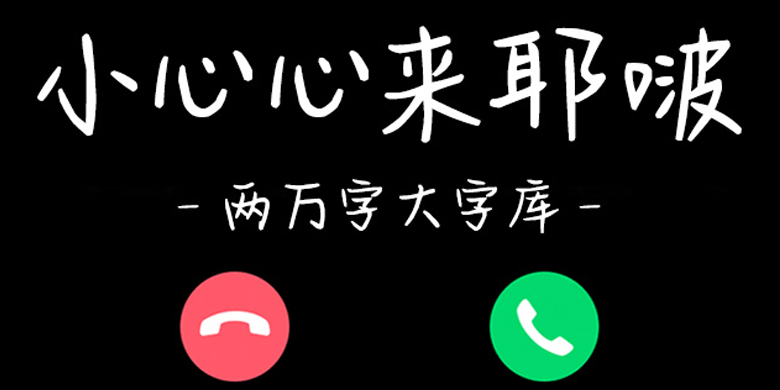
方正手迹-小心心来耶啵
字体品牌: 方正手迹 设计师:余丹 字体分类:常规书写·硬笔 字体属性:精品字 字符集:简繁扩展(GBK) 发布时间: 2020
小心心来耶波是充满青春活力的字体,你会感觉该字扑面而来的热情,然后给你比个心。适用于文艺类的书刊、品牌广告和产品包装设计,以及社交网络的个性化用字。